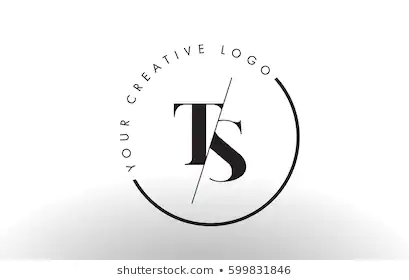
-Siberian- Skrevet 2. juni 2020 I denne logoen benyttes en S med bare én serif (øverst). Noen som vet hvilken font det er? Det er kanskje ikke en i det hele tatt - den er muligens fjernet etterpå?
bjornkn Skrevet 2. juni 2020 Tror det mest sannsynlig er en S som er manipulert ja. Fonten ser jo ellers ut som noe Bodoni-aktig?